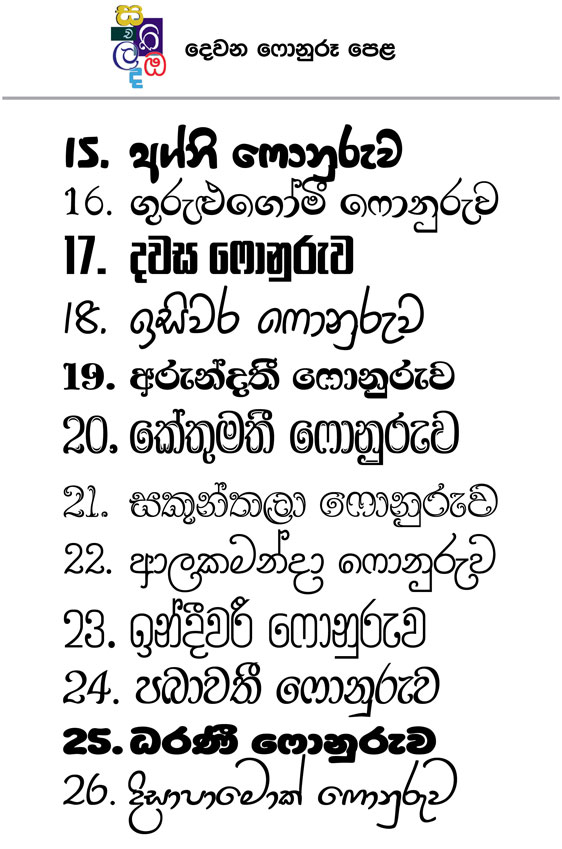
me font eke nama mokadda mcn la? download karaganna one
vectorizer Well-known member Jan 1, 2009 445 611 93 Nov 2, 2022 #5 19. Arundathi eka neda? Reactions: S_M_S and TechnWeb